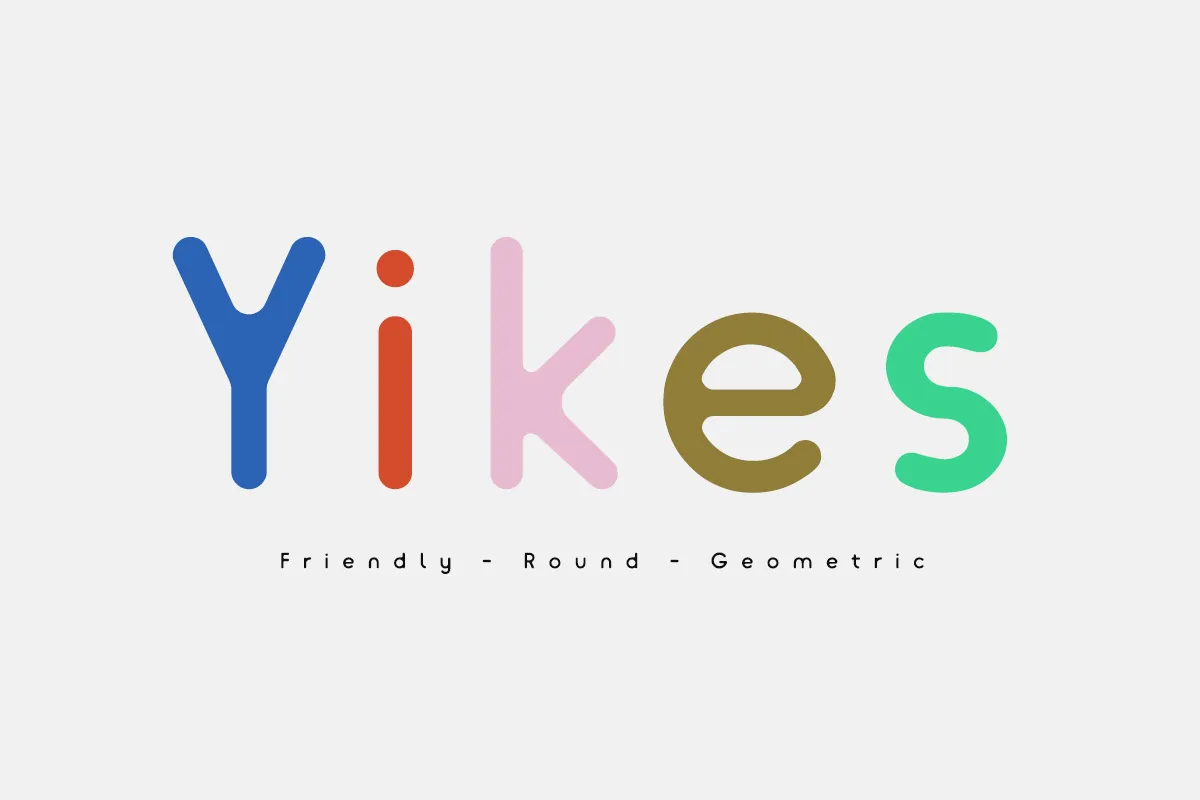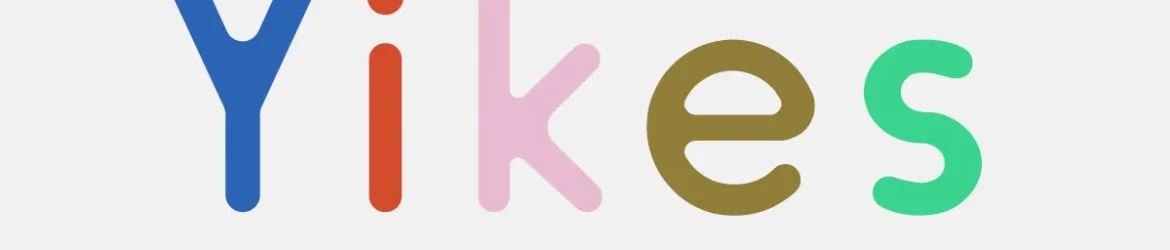
A Yikes Font é uma opção ideal para aqueles que buscam um visual moderno e alegre sem perder a simplicidade do tipo serifado. Inspirada nas formas redondas e afáveis, essa tipografia sans-serif oferece uma textura perfeita para gráficos como logotipos, headlines e materiais de propaganda. Sujeitável aos designers de logos em busca de um contraponto criativo sem abandonar a precisão que um tipo não serifado proporciona. Com formas redondas e levemente círculares que contrastam com seu formato straight-forward, a Yikes é perfeitamente adaptada para criar um efeito de simplicidade em designs modernos e vibrantes. É uma escolha inteligente para aqueles buscando adicionar um toque de frescura aos seus projetos visuais.